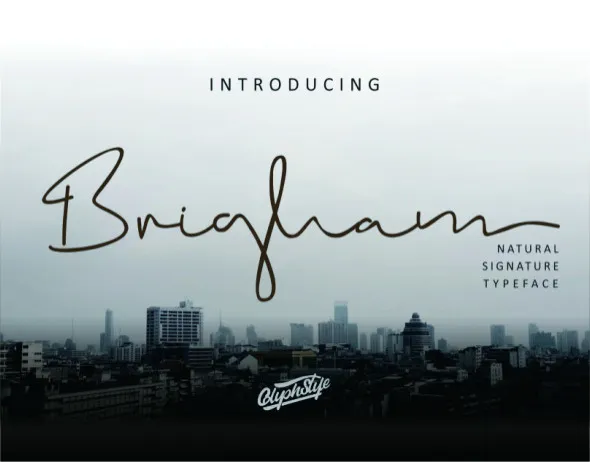
Brigham Signature Font – Download Grátis
A Brigham Signature é uma fonte de letra digital criada a mão que oferece um estilo natural e sofisticado. Suas linhas transmitem elegância luxuosa, com toques sutis de rasgos naturais produzidos pelo dedo humano. Esta font é perfeitamente adaptável para uso em diversos projetos, como branding pessoal, cartões de visitas, logotipos empresariais, embalagens, produtos, etiquetas, fotografias e até mesmo nas bordas dos documentos. Brigham Signature Script é uma escolha perfeita para qualquer projeto que deseje um toque autêntico de escrita a mão. Suas linhas fluidas combinam com estilos de personalidade distintos, tornando-a uma fonte ideal para atingir os anseios do seu público-alvo através da confiabilidade e sofisticação única deste design.